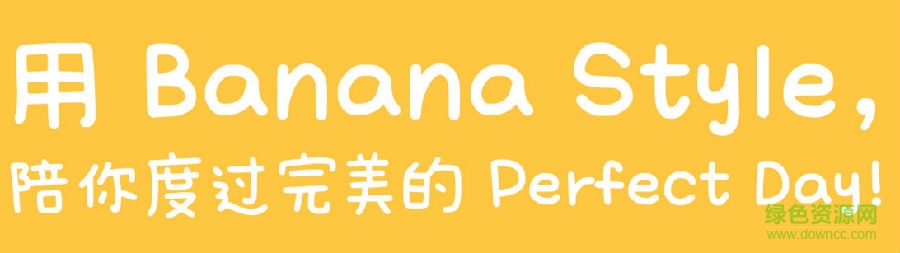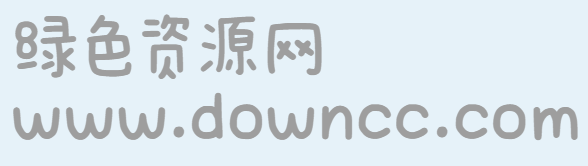
文鼎香蕉人字體是一款非常活潑可愛(ài)的漫畫風(fēng)格的書法字體,清新別致的造型讓你感受萌萌噠的輸入效果,適合于海報(bào)設(shè)計(jì)、印刷打印等行業(yè),喜歡的朋友快來(lái)綠色資源網(wǎng)你下載吧?。?/p>
文鼎DC香蕉人體_B是文鼎科技與插畫家_香蕉人(林柏辰)合作開發(fā)的手寫字型,所有的字體都是香蕉人手寫繪制,再由文鼎作字型數(shù)字化,將推出繁中Big5字集、簡(jiǎn)中GB2312+ GB12345字集的TTF字型。香蕉人體最大特色,所有的中文及英歐文,都采用不同字寬的調(diào)和字設(shè)計(jì),突顯香蕉人手寫字有點(diǎn)呆、有點(diǎn)萌,慢慢地寫、緩緩地進(jìn)步,讓香蕉人體陪著你,每天前進(jìn)一點(diǎn)點(diǎn)。